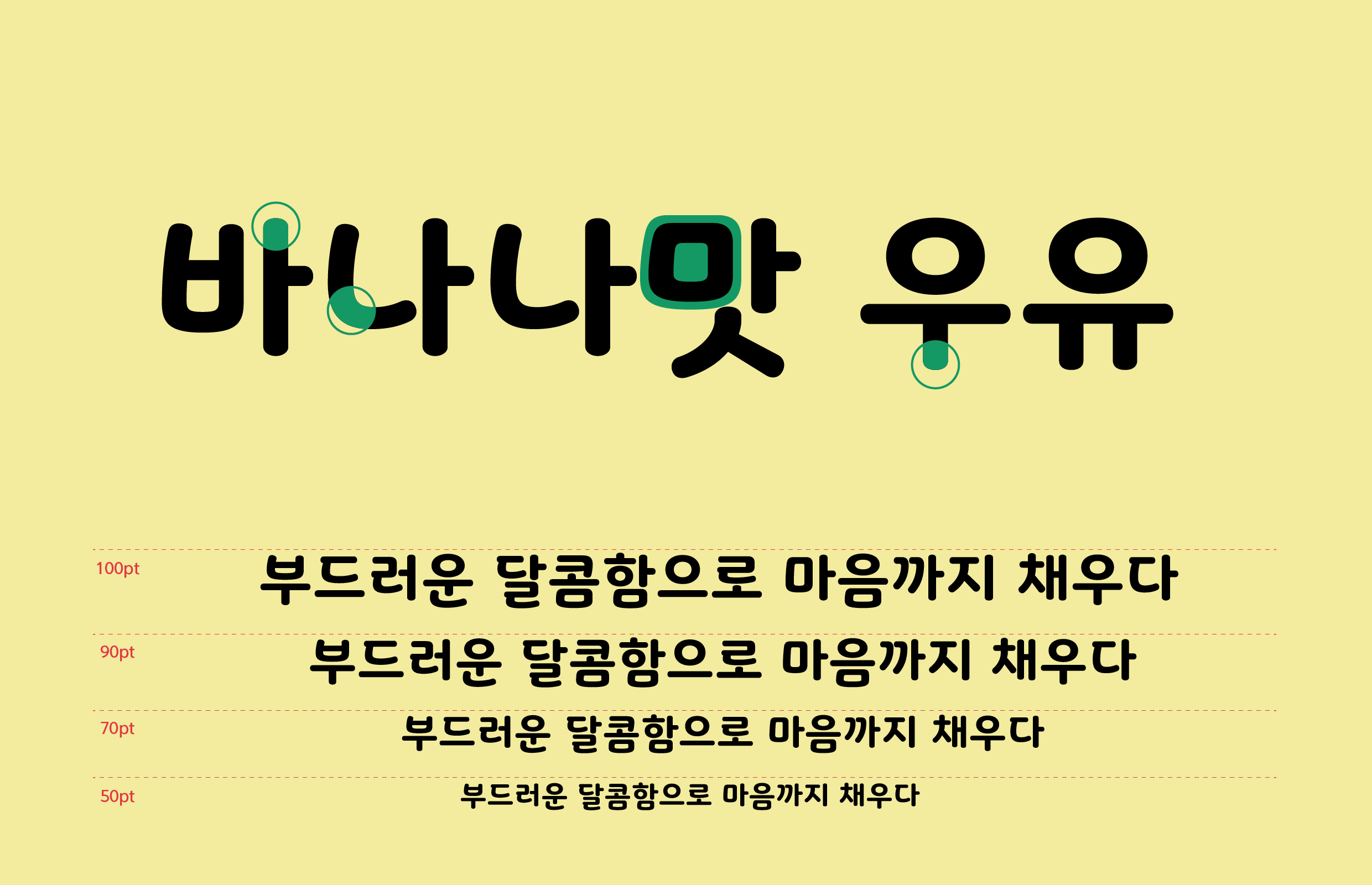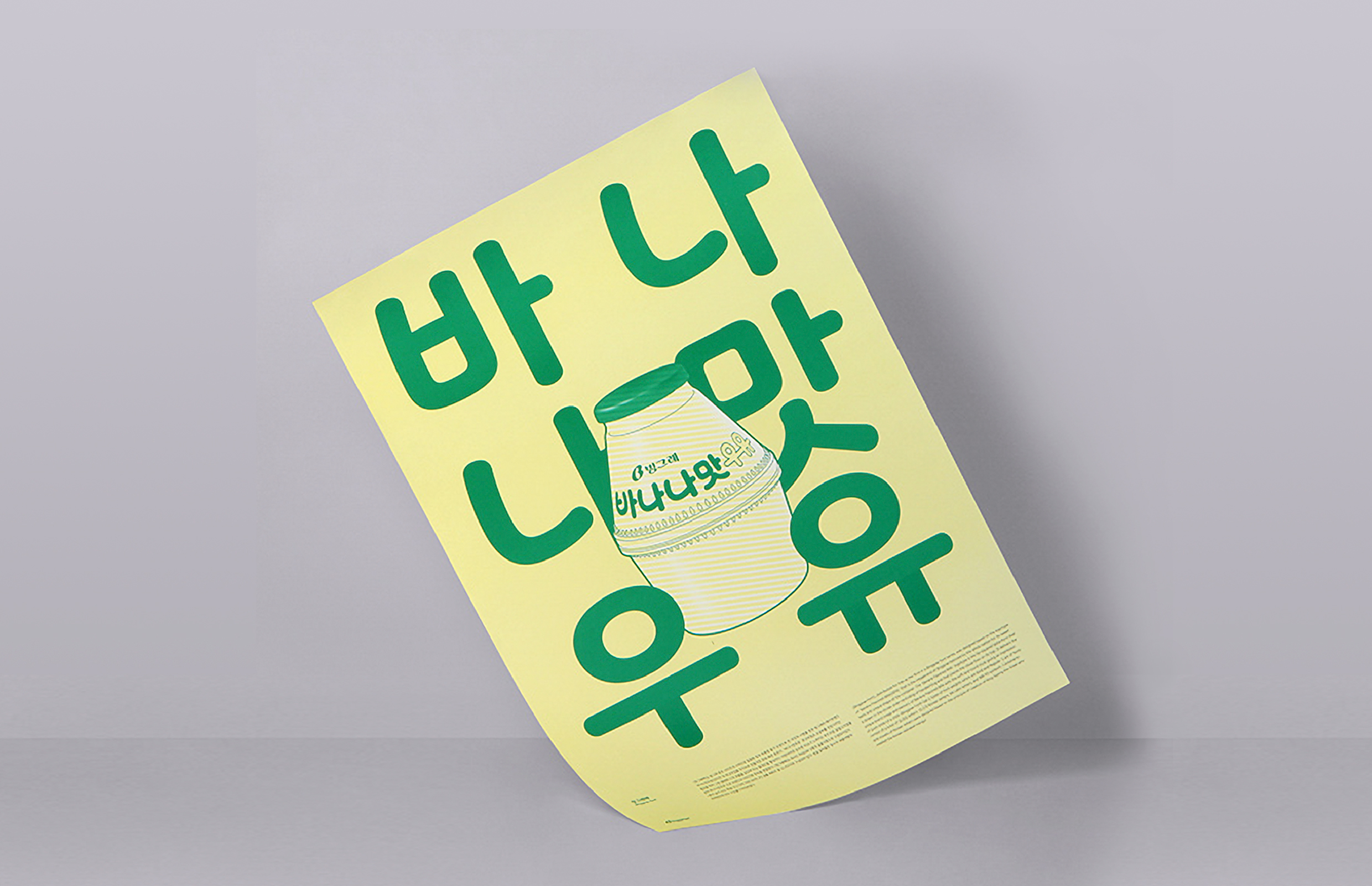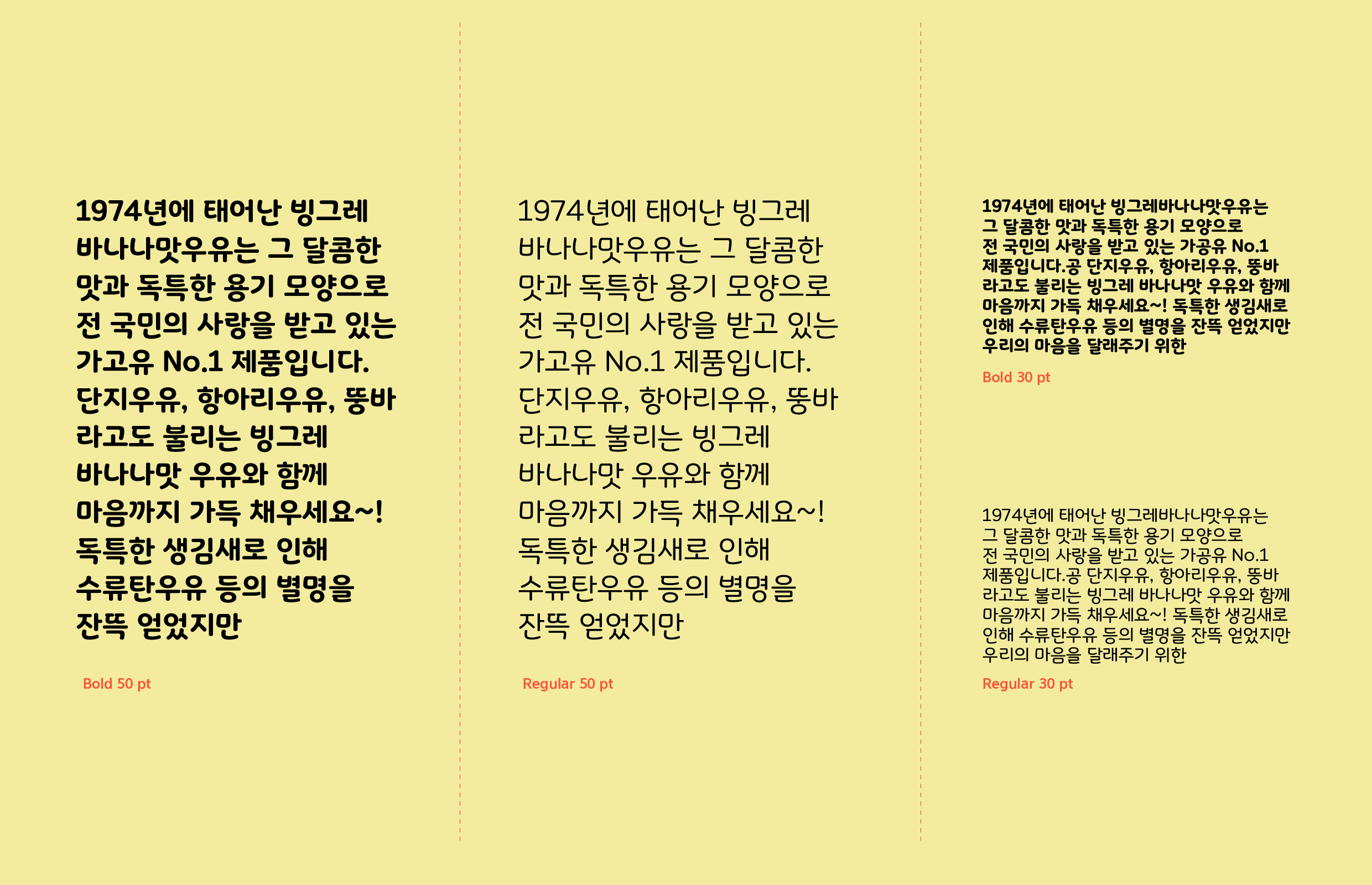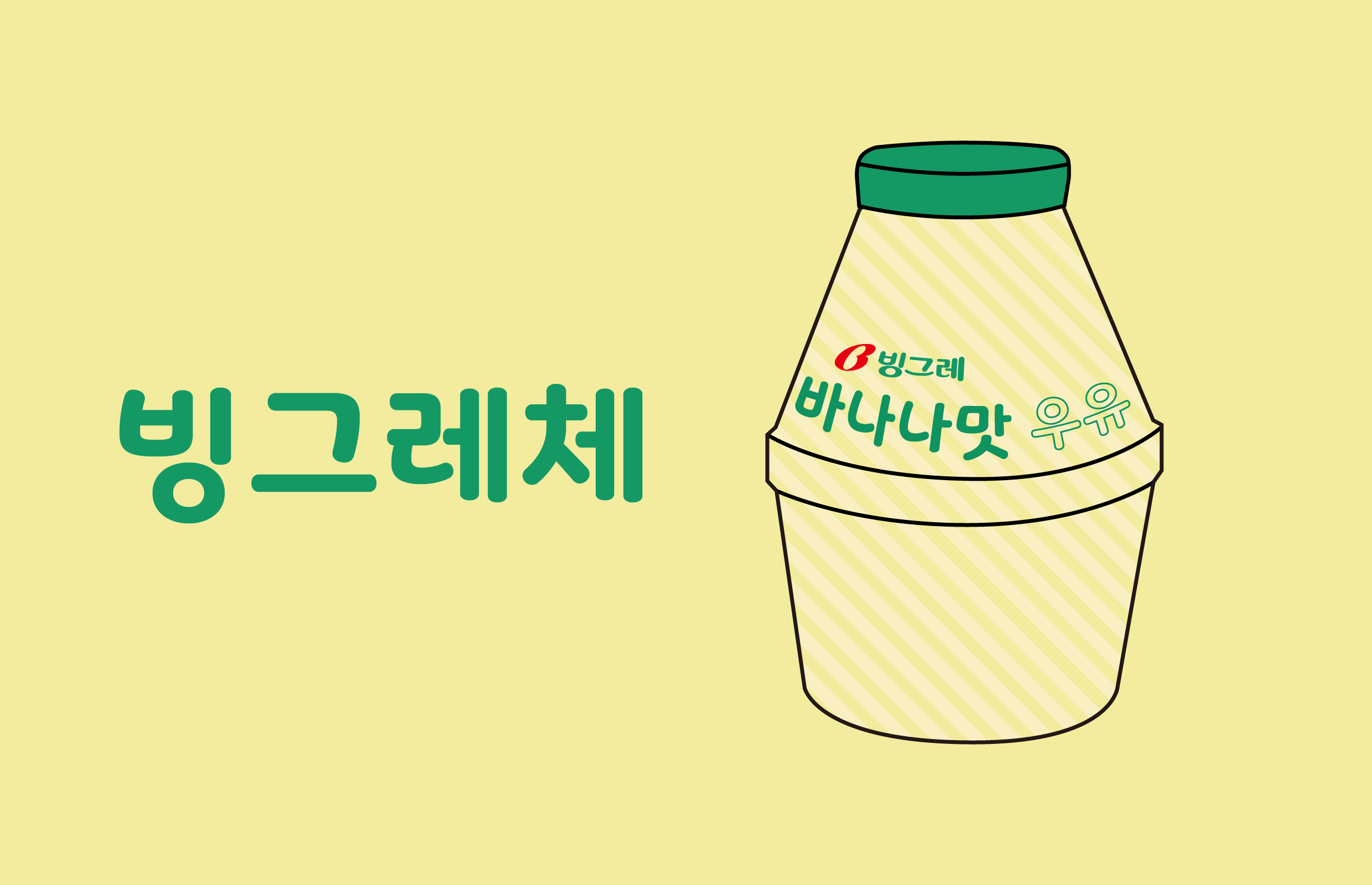
빙그레 [빙그레]
빙그레 [빙그레체]
빙그레 ‘바나나맛 우유’ 제품의 로고를 디자인 모티프로 삼은 서체. 훈민정음 제자 원리에 따라 초·중·종성 각 자소의 독립성을 유지한 형태가 특징이다. ‘빙그레’의 사전적 의미, 즉 ‘입을 약간 벌리고 소리 없이 부드럽게 웃는 모양’을 시각적으로 형상화한 글자다.